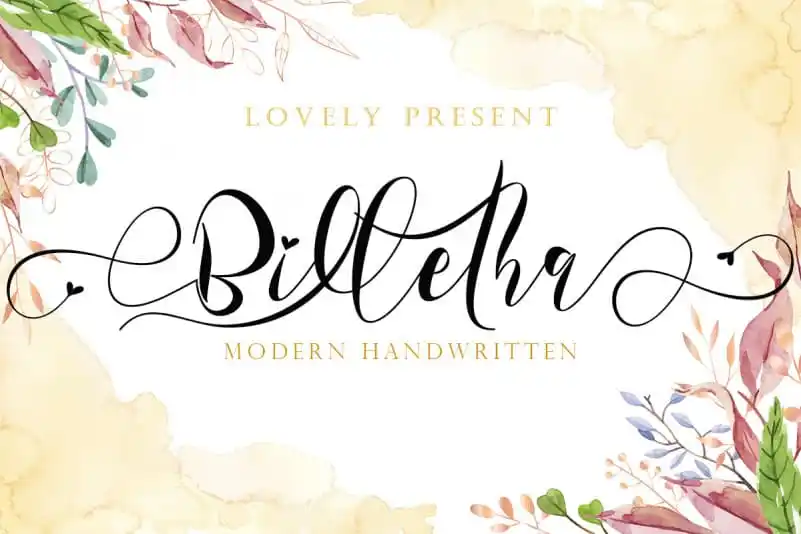
Billetha Calligraphy Font – Download Grátis
A Billetha Calligraphy Font é uma escolha perfeita para quem busca estilo sofisticado e elegância em suas produções digitais. Este é um tipo de escrita decorativa, que se destaca pela sua refinada beleza e qualidade premium. Cria-se com muito carinho e amor, oferecendo a capacidade de tornar o seu trabalho ainda mais belo e elegante. A Billetha é perfeitamente adequada para todo o tipo de necessidades relacionadas à casamento, marketing de produtos ou serviços, criação de citações e cartões de convite, desenvolvimento de logotipos e marca, atualização em momentos especiais de feriados ou status nas redes sociais, promoção e muito mais.